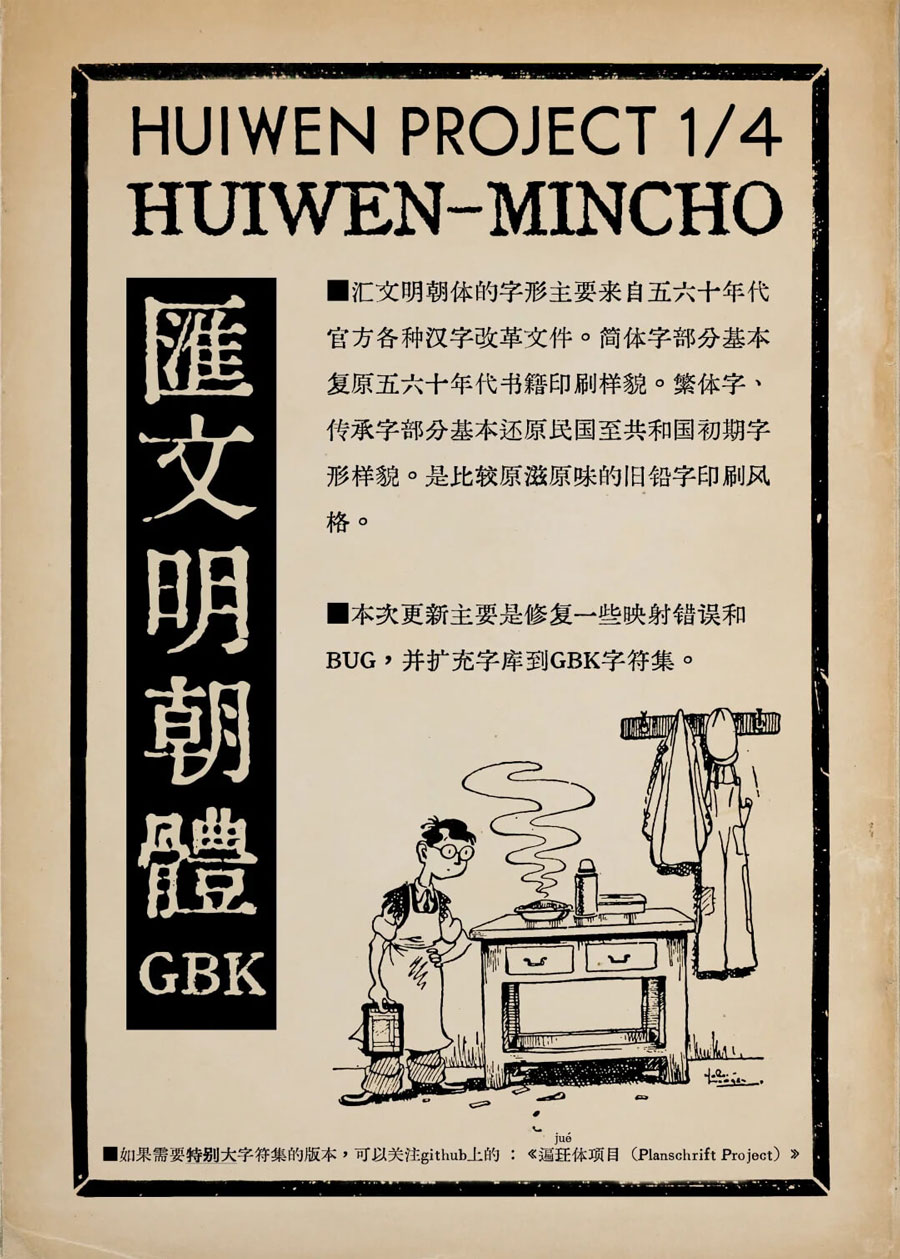
汇文明朝体GBK(Huiwen-MinchoGBK)是由网友 @特里王 开发的一款主打五六十年代旧铅字印刷风格的可免费商用的明朝体(宋体),是汇文明朝体的 GBK 扩展版本。
原版的汇文明朝体制作始于2019 年 1 月,是通过扫描《文汇报》上的《汉字简化方案草案》等资料,然后不断收集、扫描五六十年代官方汉字改革文件,最后汇总挑选形成基础字形。而汇文明朝体 GBK 是为了修复原版的映射错误和 BUG,同时将字符集从 GB2312 扩充到 GBK 全字符集,大幅提升了生僻字覆盖能力。
因为汇文明朝体GBK 模拟的是旧印刷效果,所以小字号显示时清晰度可能不如现代宋体,所以建议多用于复古风格场景,如古籍整理、历史文献复刻、传统文学排版或者书店、茶馆、传统工艺的品牌设计等。